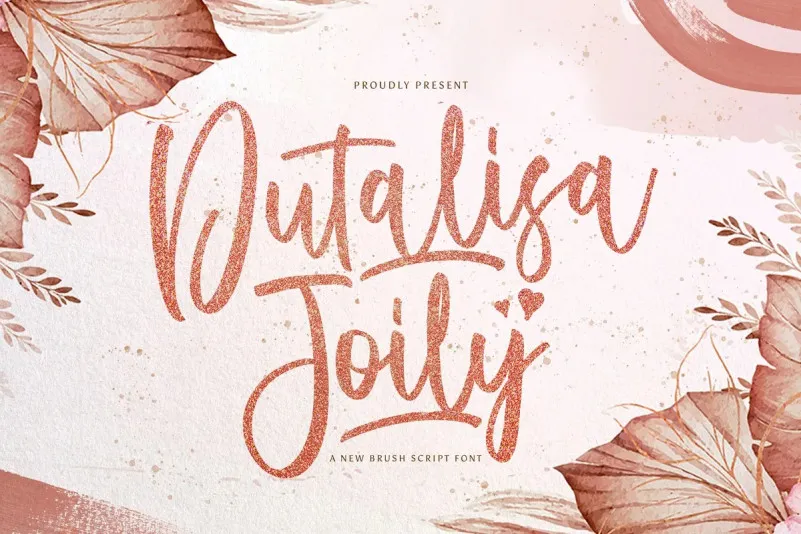
Dutalisa Joily Brush Font – Download Grátis
A Dutalisa Joily Brush Font é uma fonte script que traz a moderna estética orgânica. Ela se destaca por seu estilo elegante e despojado, com características bem equilibradas e arquitetura de letras sofisticada. Esta fonte se adapta perfeitamente para um vasto leque de ideias criativas. Quando adicionada a suas projetos, é fácil notar como ela transforma essas idéias em algo vibrante e imersivo. Com sua aparência moderna e orgânica, esta Dutalisa Joily Brush Font é perfeita para os designers que procuram uma solução de letra que se destaque sem abandonar a simplicidade elegante. Ela combina o estilo contemporâneo dos arquivos brush com um toque refinado que pode transformar qualquer projeto em algo único e memorável, tornando-as ideais para criações de identidades visuais, design editorial ou qualquer aplicação onde um touch distintivo seja importante.